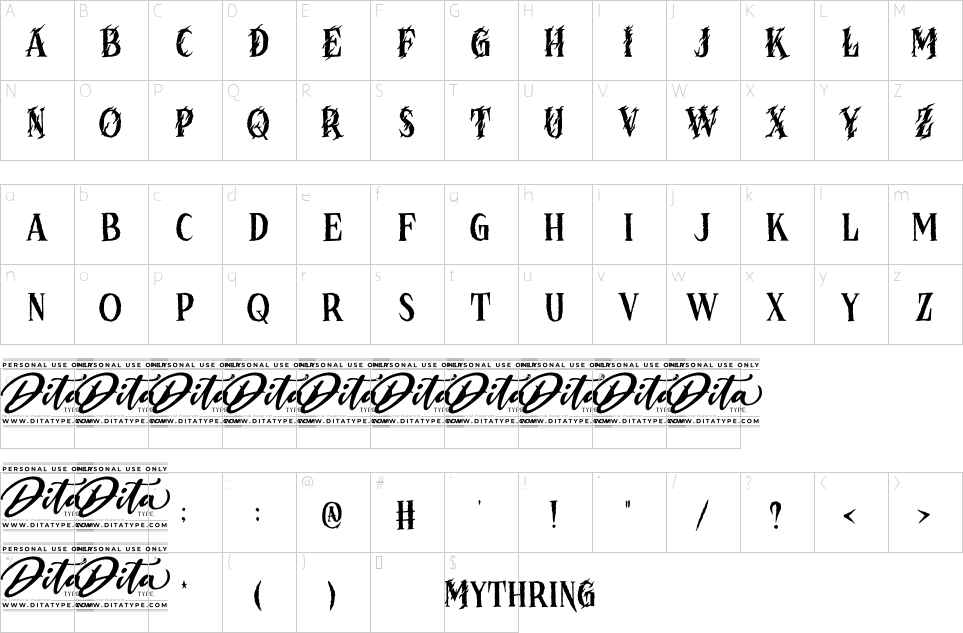
Descubra a beleza do design em Mythring, uma elegante fonte grátis criada pela Dita Type. Esta fonte oferece uma paleta de características que vão desde linhas finas até linhas grossas, tornando-a ideal para um vasto leque de projetos, desde gráficos de negócios até publicações de arte digital. Sua versatilidade e qualidade a fazem uma escolha ótima para quem procura uma fonte de alta qualidade sem precisar gastar dinheiro. Não hesite em baixar Mythring, uma fonte de alta qualidade disponível de graça para usuários de Windows e Mac. Com uma aparência moderna e sofisticada, Mythring adicionará um toque único e de alta qualidade a qualquer projeto. Ative a curiosidade e tente agora!